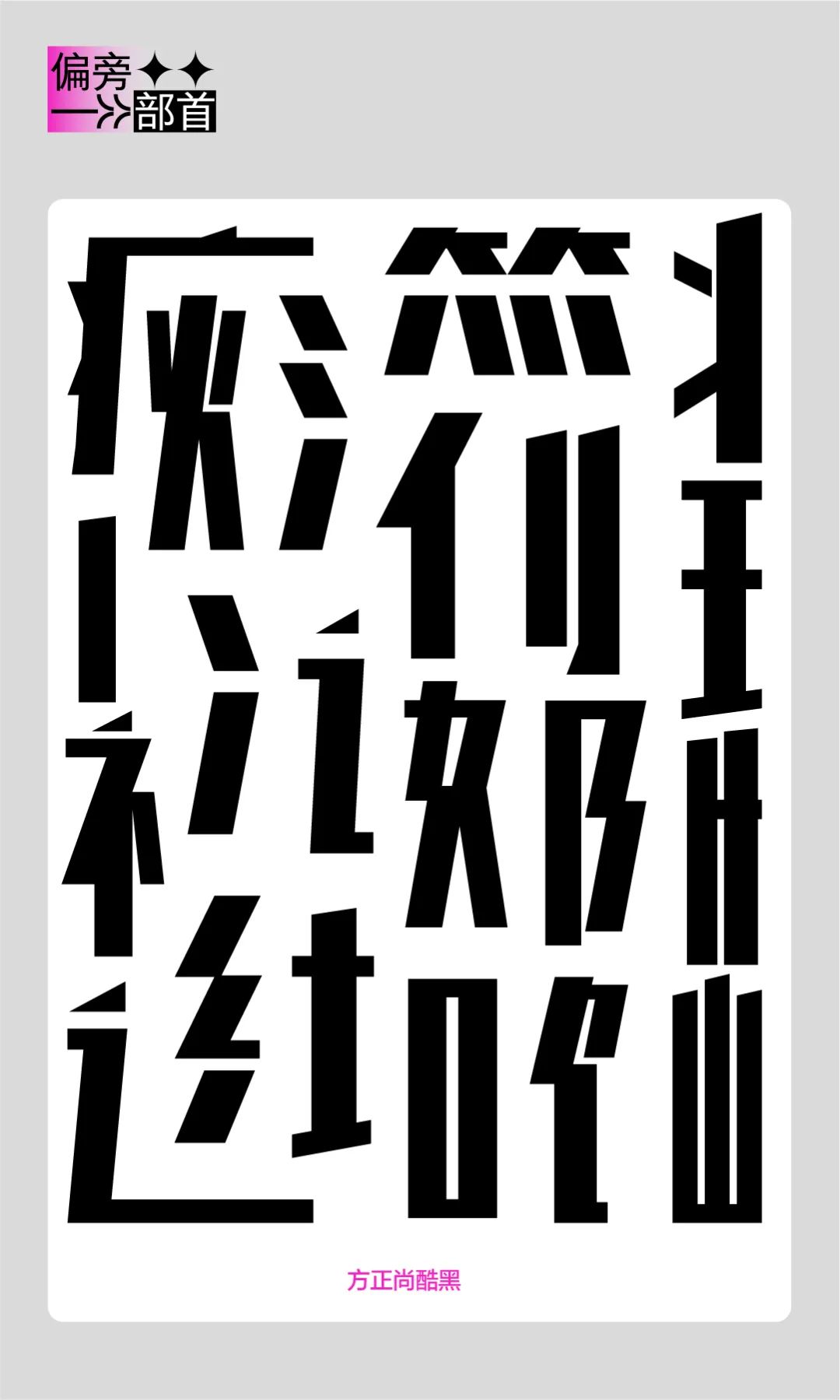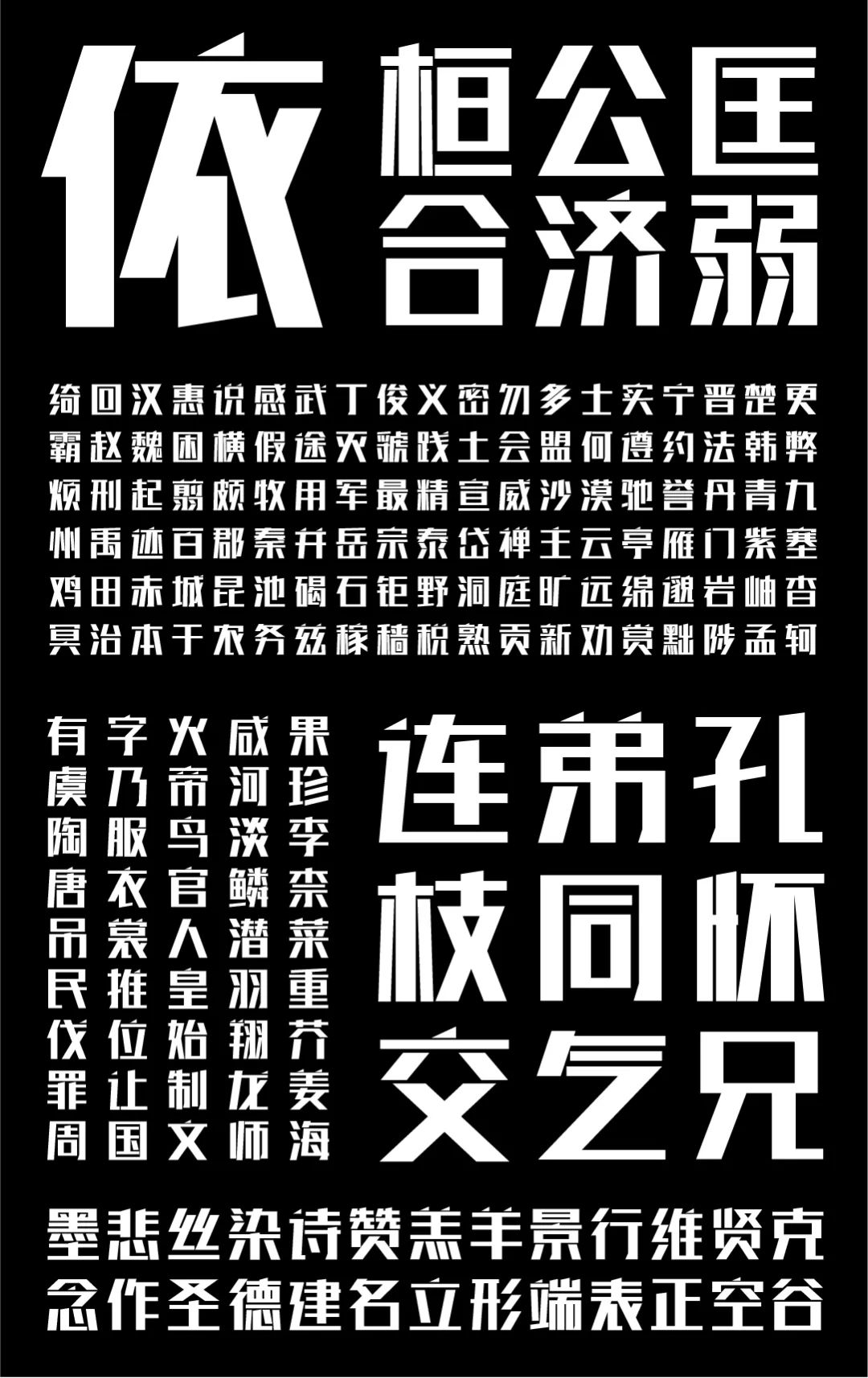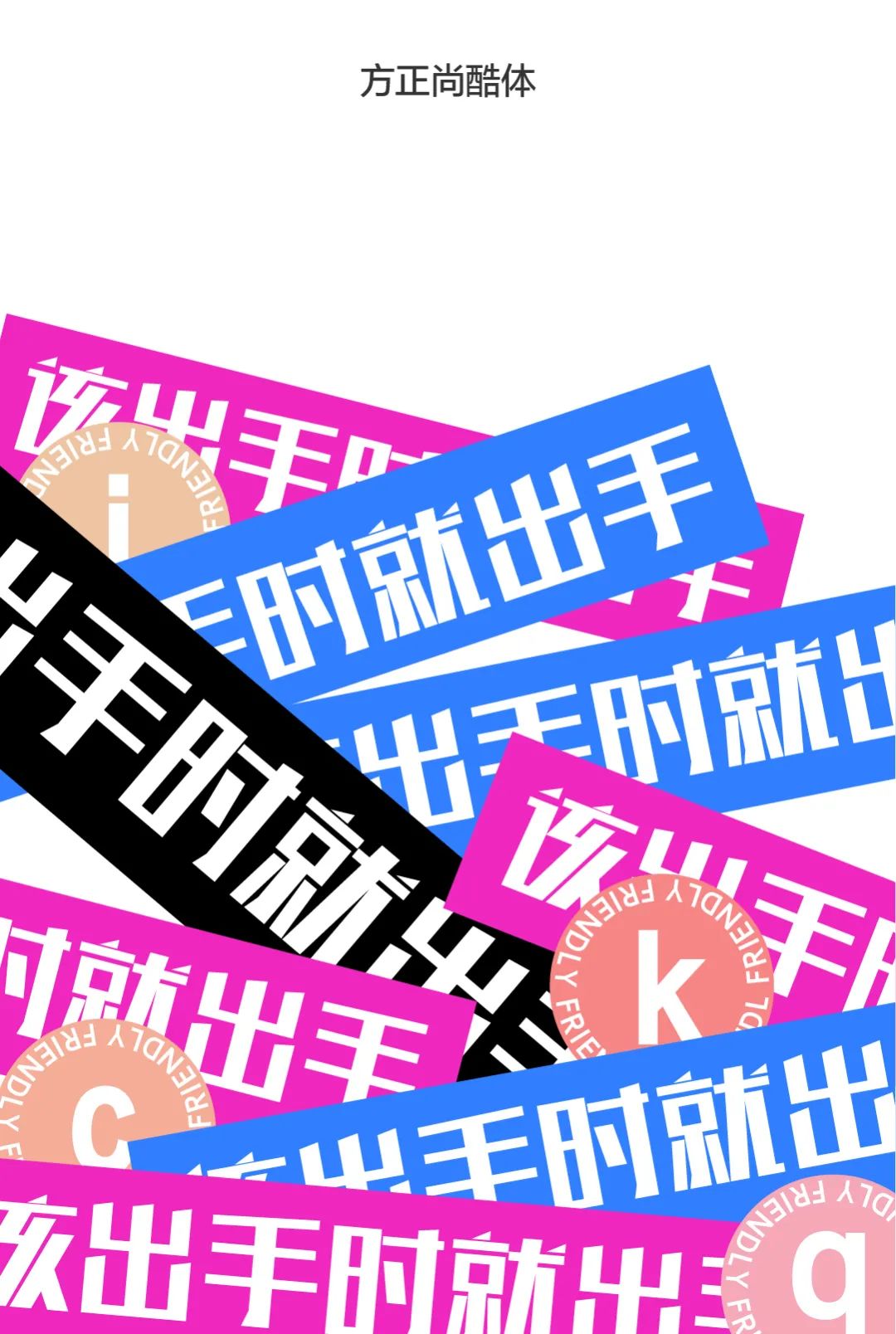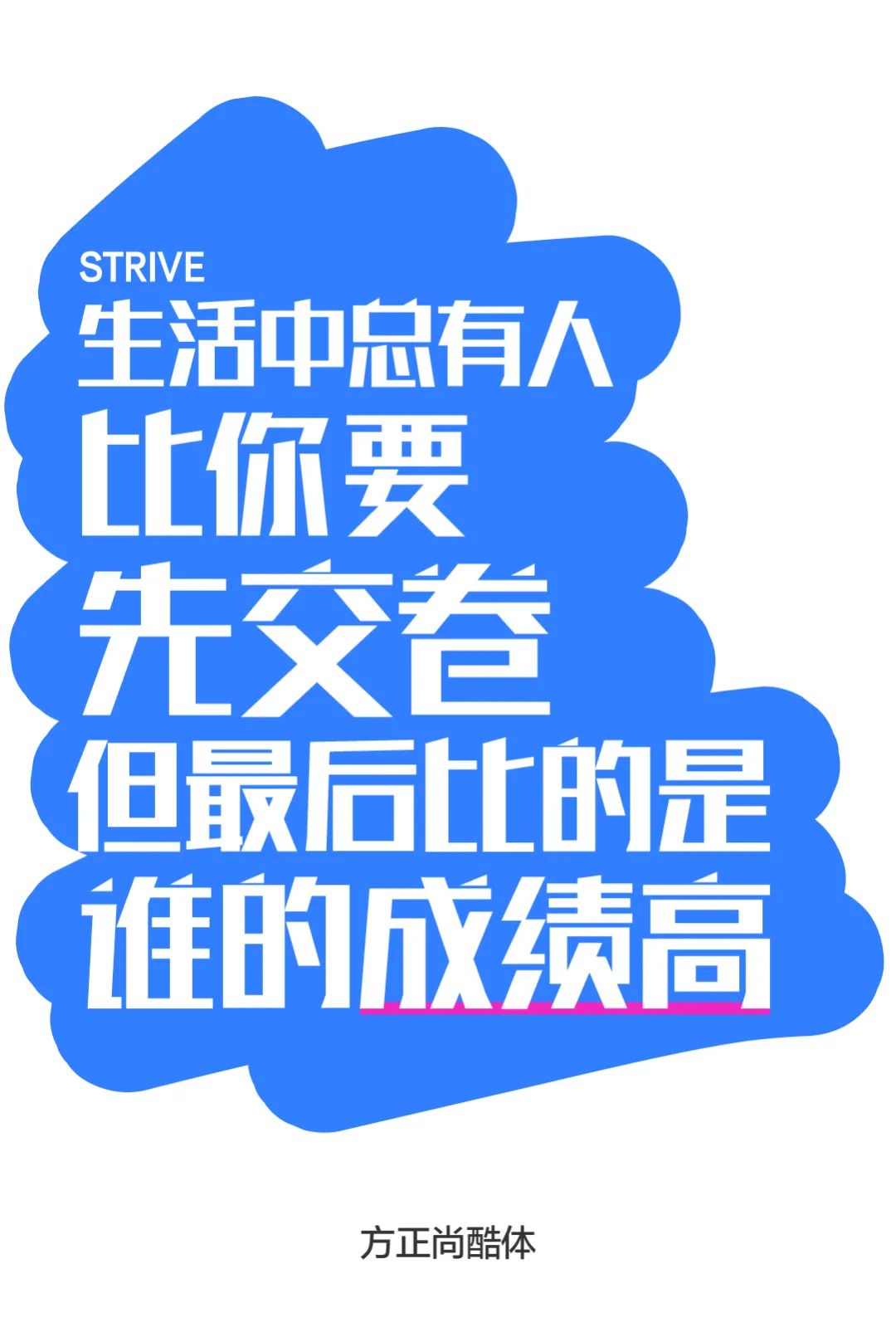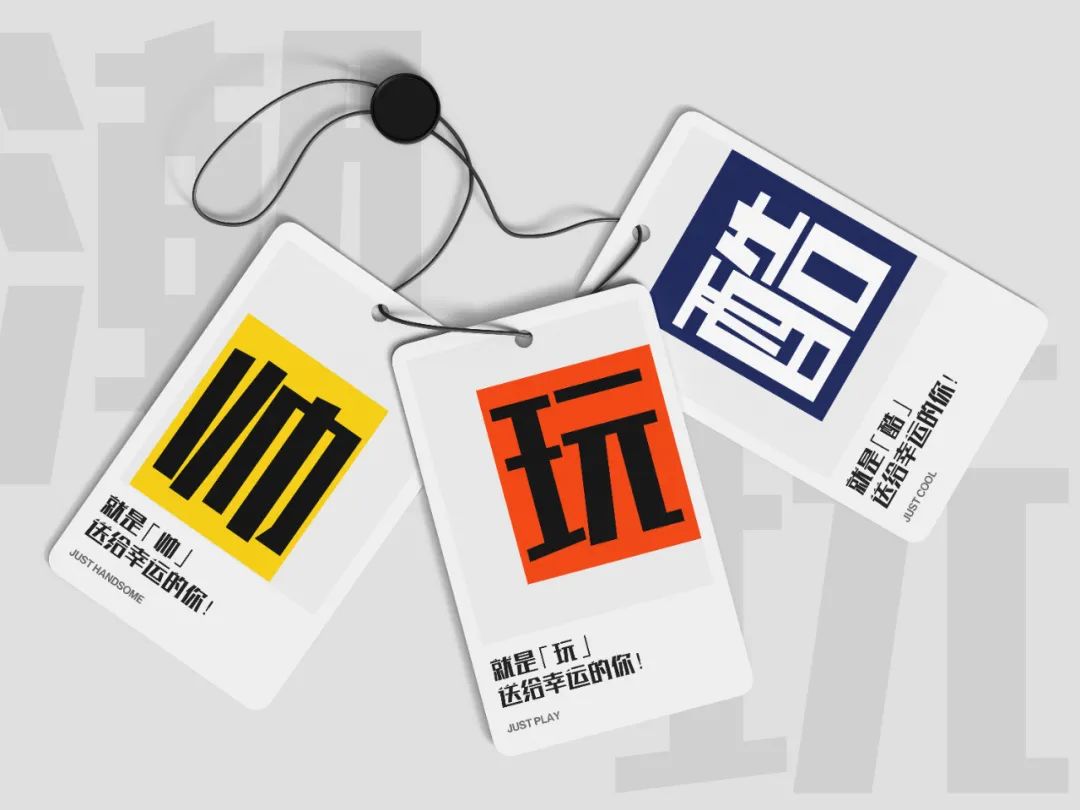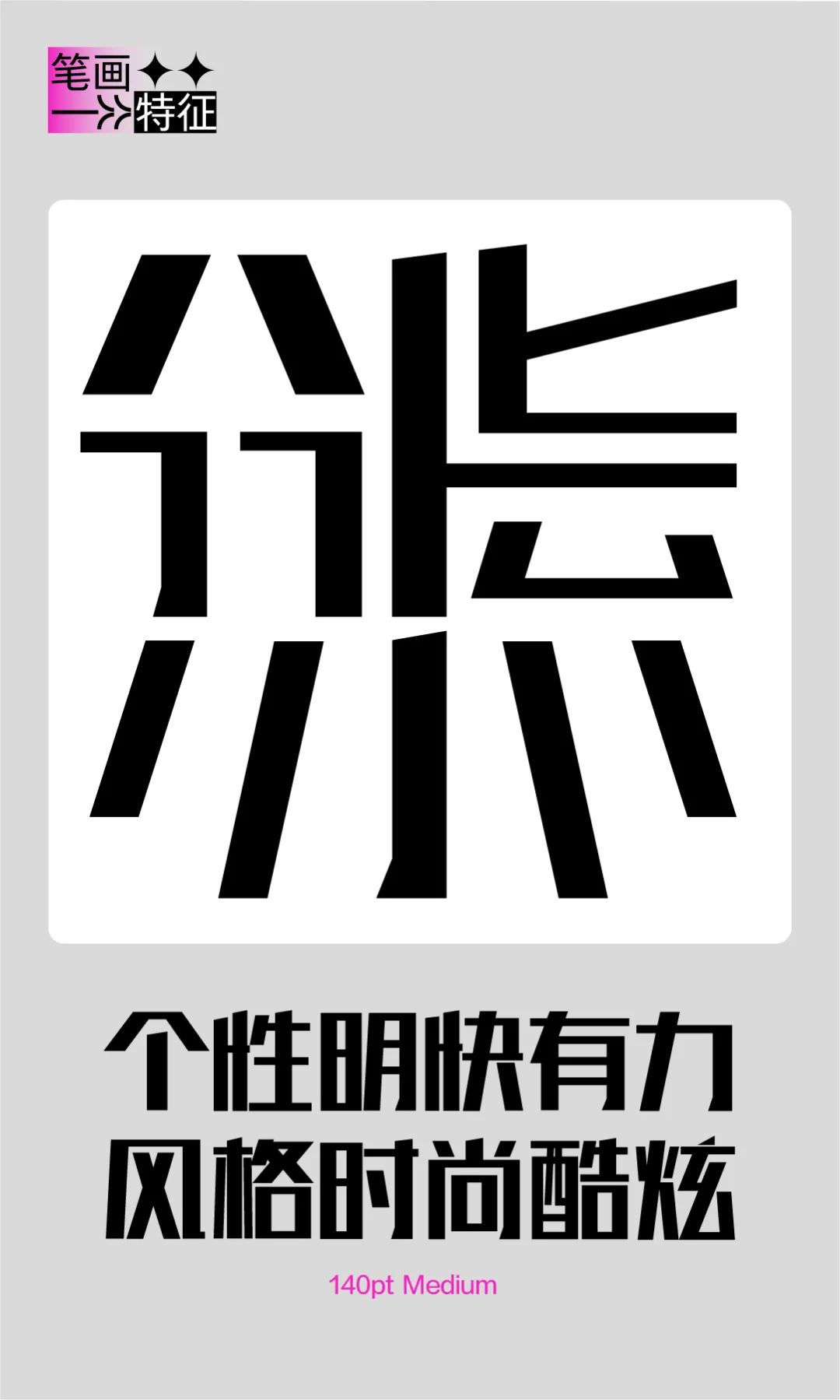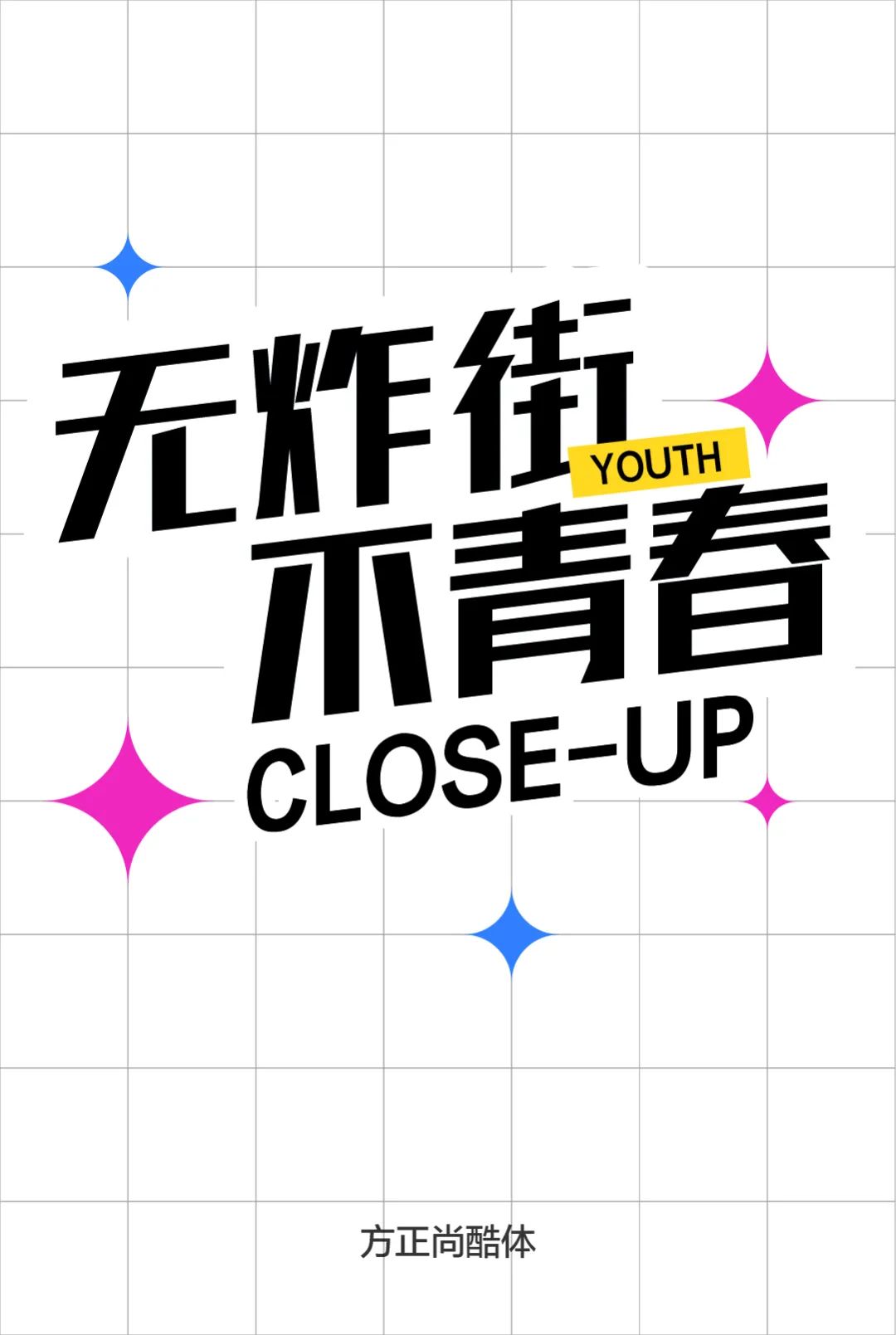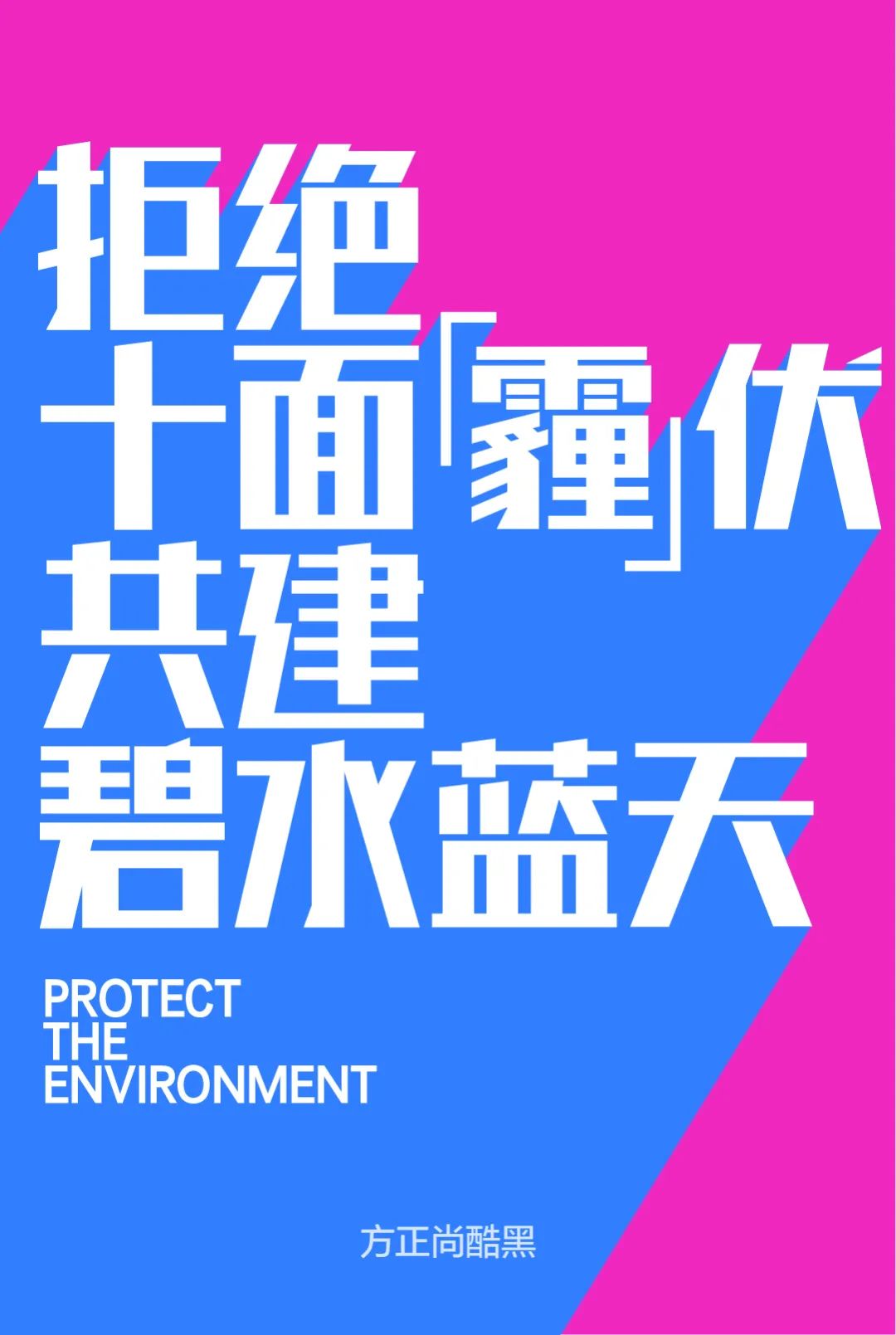
方正尚酷体
方正尚酷体,这款字体结构工整、笔画清晰,兼顾美观与易读性,适用于标题、正文、海报、包装、LOGO 等多种场景。字形优雅稳定,风格百搭耐看,适配日常排版与创意设计,让文字呈现更舒适、更具质感。方正尚酷体一笔一画,皆是细节,以均衡的比例、流畅的线条打造舒适视觉体验,字形端正大气,风格简约现代。无论是商业设计、品牌宣传还是日常排版,都能轻松驾驭,让文字更有格调与力量。方正尚酷体字体下载。
字体品牌: 方正字库 设计师:郝君军 字体分类:创意字体 字体属性:精品字 字符集:大陆简体(GB2312-80) 发布时间: 2013
方正尚酷是一款纯几何化的创意字体。这款字体抛弃笔画中的弧线,将笔画凝练成直线几何图形,多数笔画呈平行四边形,并弱化点和钩,用小三角形代替。采用大字面,横细竖粗,重心上提,显得字形稳定坚实。方正尚酷的个性明快有力,风格时尚酷炫,适用于书籍、杂志的标题,以及潮流类的广告和产品包装设计。
方正尚酷体打破了传统字体的笔形和结构,将笔画凝练为简练的几何图形,使字型更趋向于图形化处理,
抛弃弧线细节,追求用最简洁的设计元素营造丰富而统一的视觉氛围。
大字面、横细竖粗的笔画结构,保证了字面的稳定性;
上提的重心,又满足了字面的美观性,达到身短腿长的视觉效果;
点与勾的结构处理为三角形,增加了字体的灵动性和犀利感,使字体更有性格与个性。
对时尚感与力量感的塑造,恰如这款字体“尚酷”一名。
方正尚酷的个性明快有力,风格时尚酷炫,适用于潮流类品牌的广告、产品包装设计,
同时可作为标题字体在海报、书籍、杂志中使用。